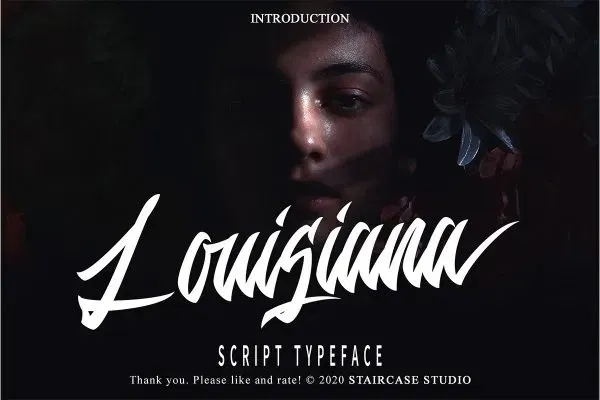
A Louisiana Font é uma elegante tipografia brush que traz para você um estilo natural e bold em uma serifada script. Criado pela StairCaseLab, essa fonte adicionalmente inclui extras de swash, oferecendo-lhe letras e números perfeitos para suas necessidades de projeto. Com sua elegância e fidelidade ao estilo, a Louisiana Font é ideal tanto para Logotipos quanto para Design de Marca e identificação visual. Suas linhas suaves e detalhes finos fazem-a uma escolha ótima para projetos como t-shirts e roupas, cartazes, postagens na internet ou mesmo designs publicitários. Ela se destaca em qualquer projeto que você tenha no seu armário de design digital. Experimente a Louisiana Font agora e transforme suas criações digitais num verdadeiro trabalho de arte.